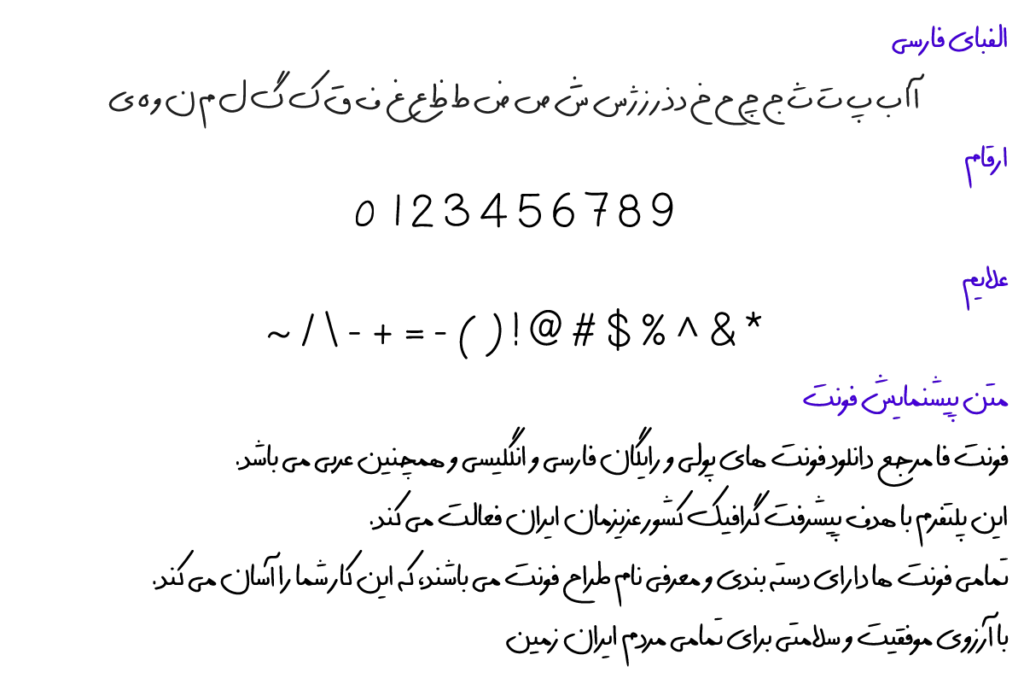
فونت فارسی پاییز - Paeez
توضیحات و معرفی فونت پاییز
فونت فارسی پاییز ( Paeez ) از مجموعه فونت های Digi می باشد، همچنان نوع فونت دست نویس می باشد.
فونت شگفت انگیز و زیبای فوق توسط مهدی برقگیر در سال 1399 طراحی و ساخته شده است.
همچنان فونت در یک وزن معمولی است.
• Paeez Regular